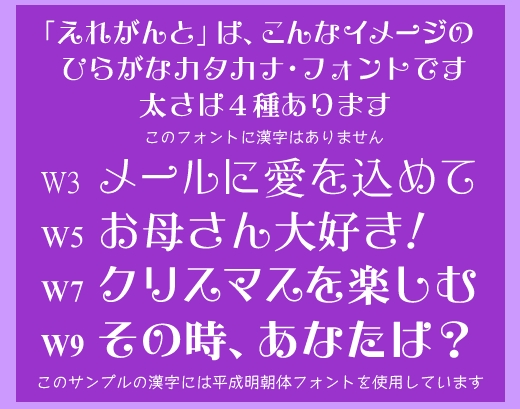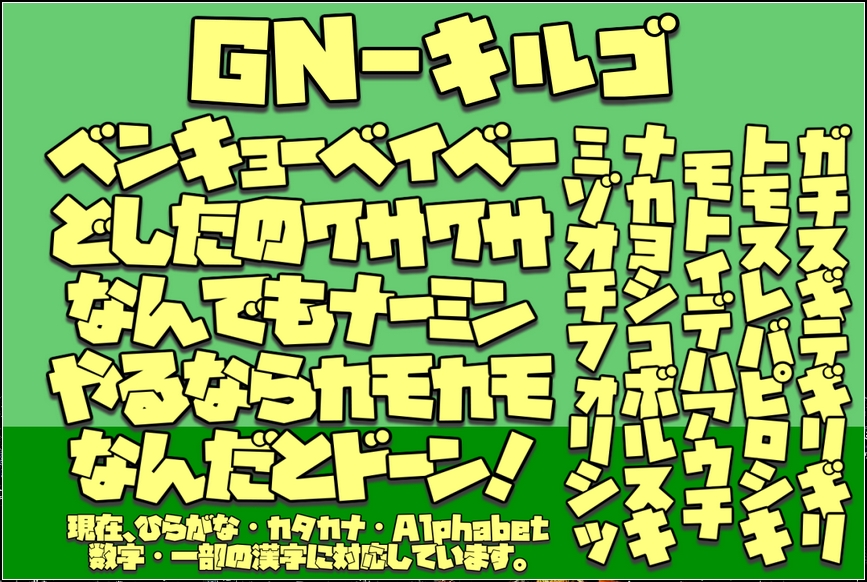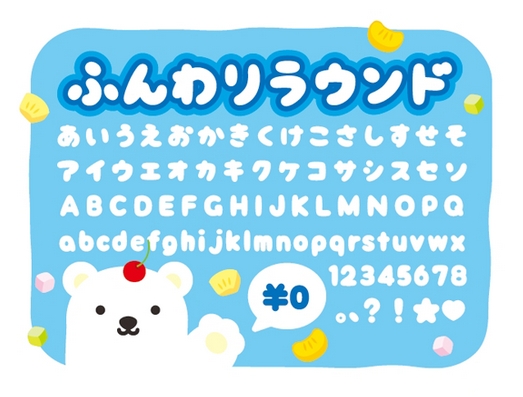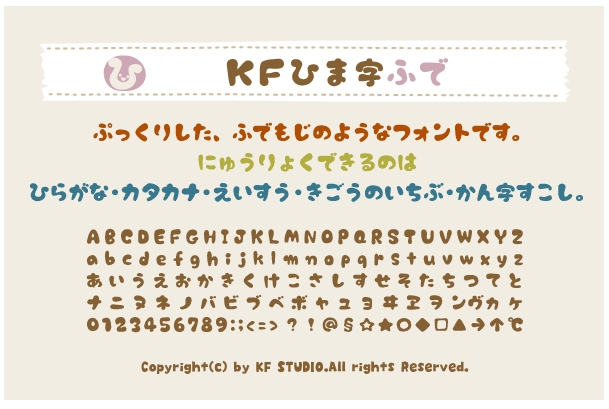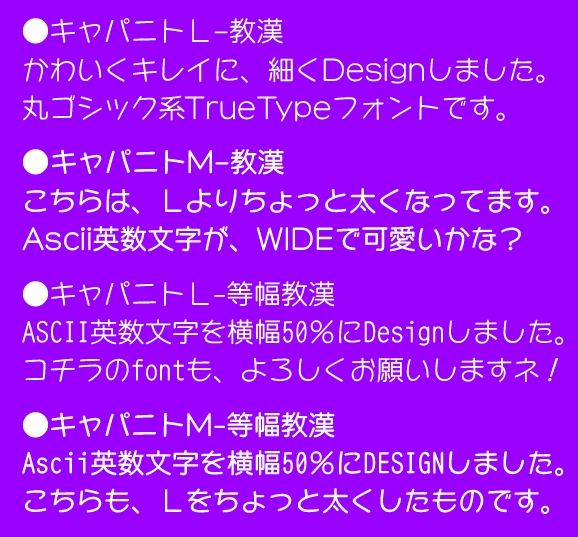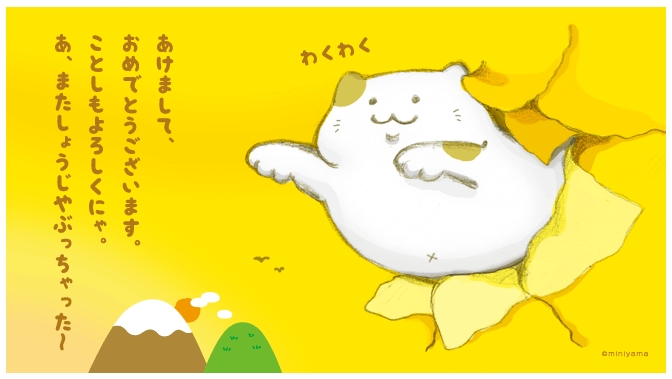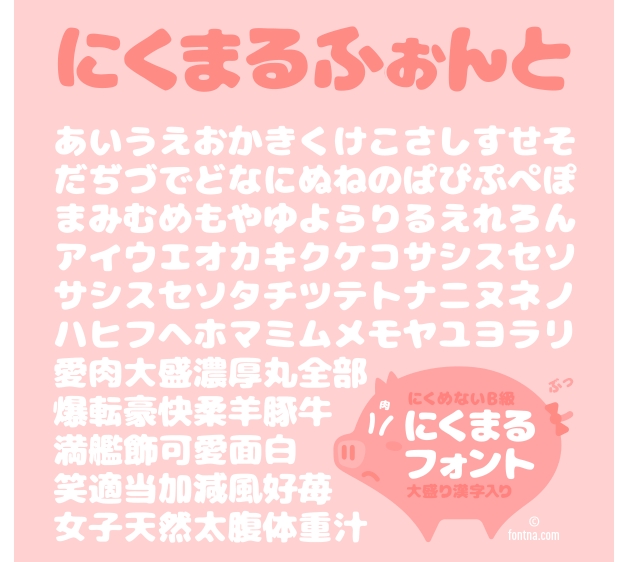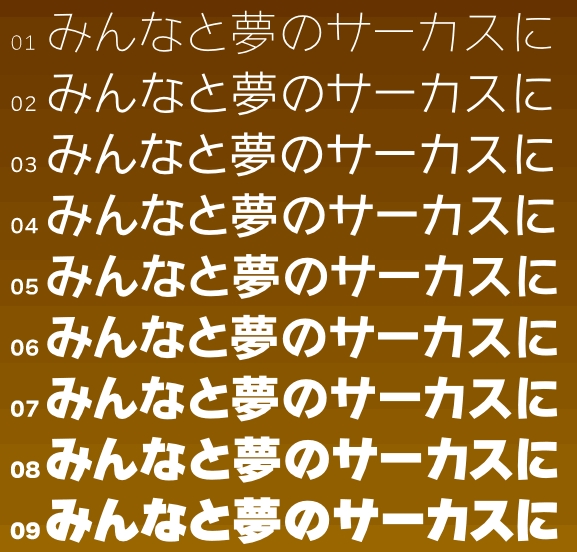
クリスマスに使えるフリー日本語フォント 無料で商用利用可 ひらがな カタカナ 英数字 漢字
もうすぐ楽しいクリスマス。
今年のクリスマスの予定、決まりましたか?
ここでは楽しいクリスマスに向けて、
クリスマスに合った日本語フォントなどを見てみましょう。
ひらがな、カタカナ、英数に漢字と使えて、無料な上に商用利用可のフォントってあるかな~、なんて探してみると、これが結構あるんですね~。
こんなに色々なフォントが、クリスマスのパーティーからクリスマス用のちらしやポスター、クリスマスの飾りつけなどに利用できて嬉しいです。
あなたのイメージに合ったフォント、見つかると良いですね。
楽しいクリスマスが送れますように。Merry Christmas !
漢字は非対応のフォントたち
まずは漢字は使えないけど、これでも十分クリスマスな雰囲気!
といったフォントたちを見てみましょう。
ふんわりラウンド
こんなに可愛いフォントがあるんです。
丸っこくて愛らしい、クリスマスの暖かさを伝えるにはぴったりかも。
タイトルなどに力を発揮しそう。
mini わくわく
大人から子どもまで楽しめる、ちょっと手書き風のかわいいフォント。
クリスマスには、暖かなイメージを幅広い層向けに使えますね。
KFひま字ふで
ぷっくりとした筆文字のような暖かなフォント。
クリスマスの寒い夜も、こんな字を見ればちょっとホッコリできるかも。
漢字も対応のフォントたち
ここからは漢字も対応のフォントたち。
貴方のクリスマスに合ったもの、あるかな?
にくまるフォント
丸くてふくよかな暖かい文字。
クリスマスとかパーティー用の文字として使ってみると面白いですね。
えれがんと
文字の一部がクルンとなった、丸いアクセントの楽しいデザイン。
ちょっといたずらっぽい可愛いフォント、クリスマスには、特にタイトルなどに役立ちそう。
キャパニト
綺麗で全体に整った文字ですね。
クリスマスに使ってみたいフォントの1つ。
わんぱくルイカ
はっきり・くっきりした親しみやすい「かな文字」と、落ちついた雰囲気の「漢字」が特徴のフォント。明るく元気なイメージと気どらないストレートな感じがクリスマスには良く合いそうですね。
GN キルゴ
とってもユニークなフォントです。
クリスマスの明るく元気な様子にはうってつけ?
いかがでした?
こんな楽しいフォントたちと一緒に Merry Christmas ! ^◇^)